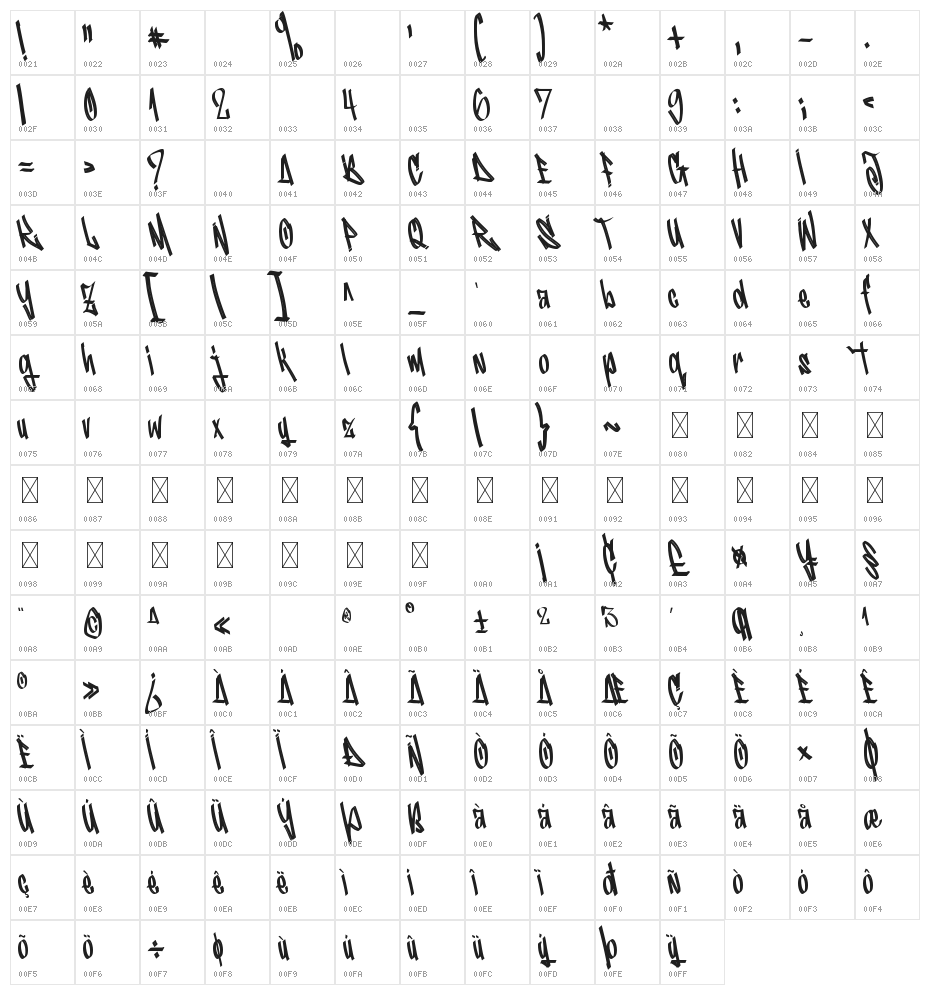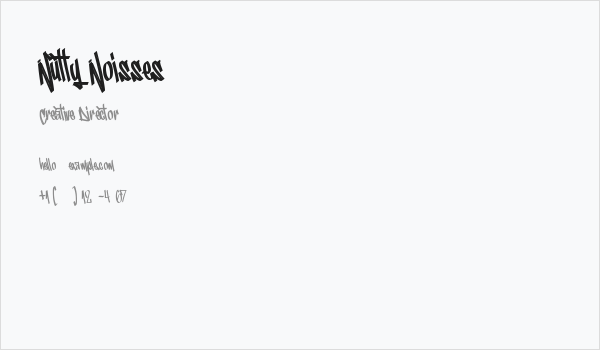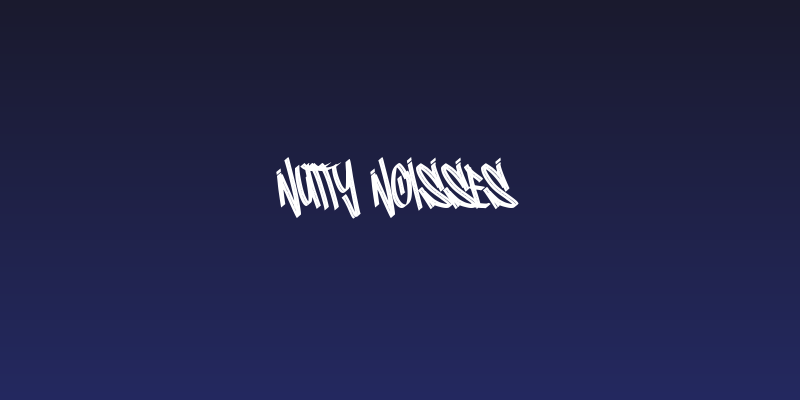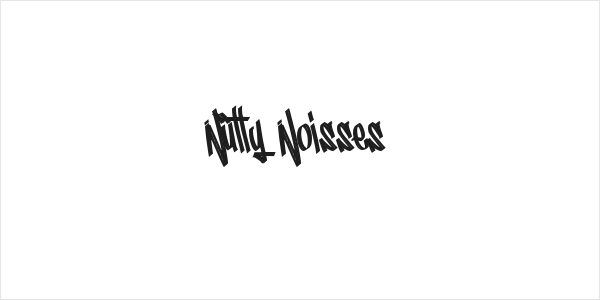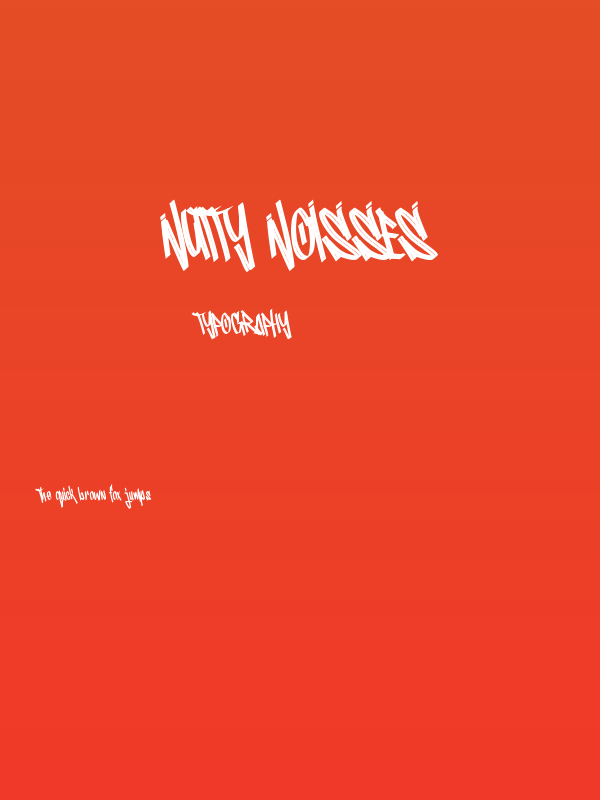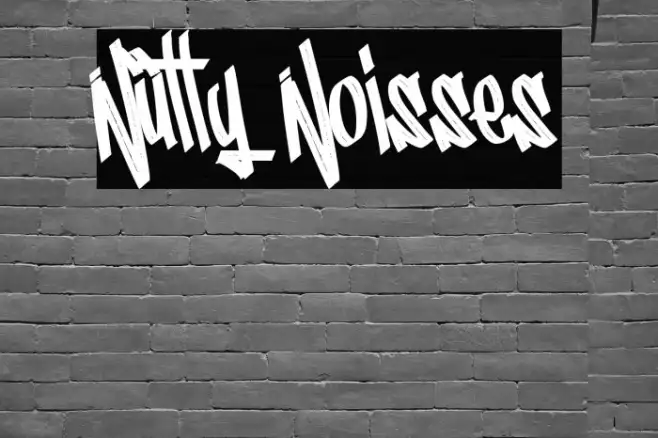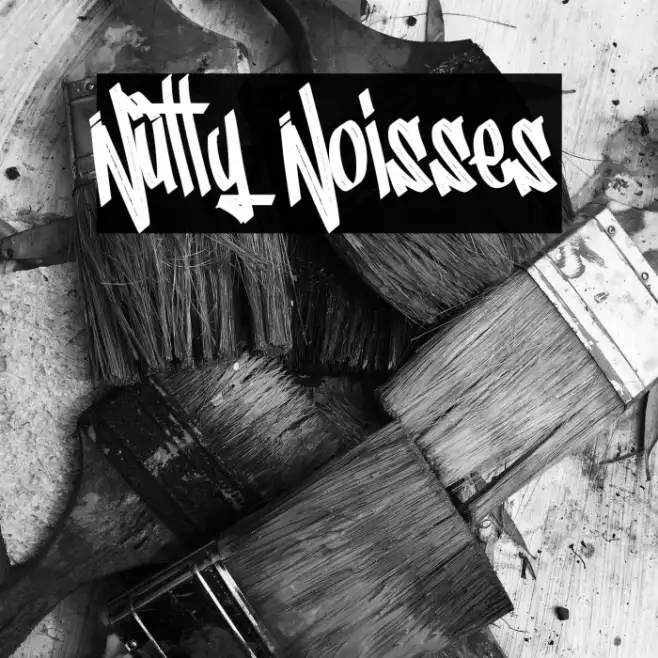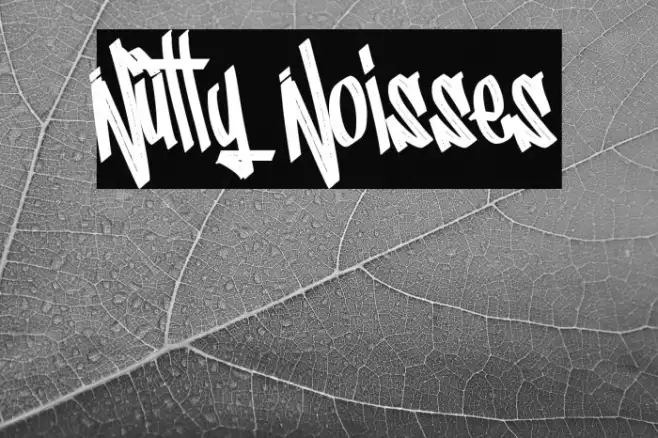
Nutty Noisses Font
✎ Graffiti
| Gesamtstil | Modern, Urban, Edgy |
| Vorgeschlagene Projekte | Ideal for street art-inspired designs, music album covers, urban-themed posters, and edgy branding projects. |